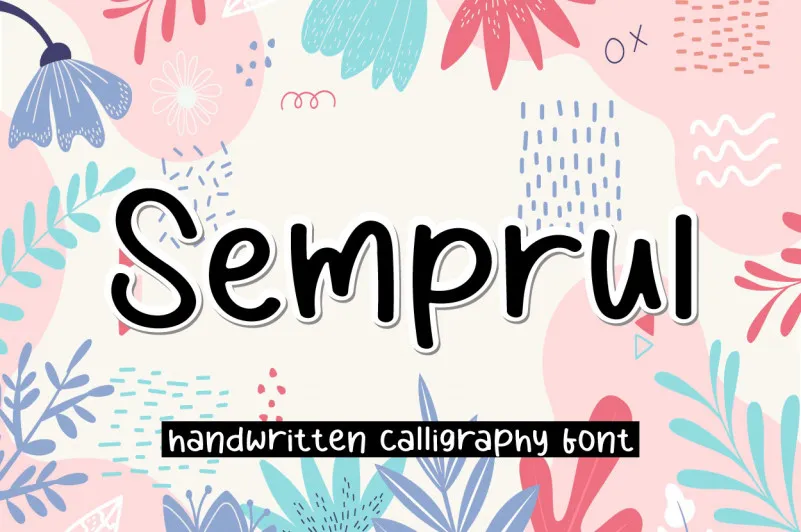
Semprul Script Font – Fonte Grátis
Semprul Script Font
A fonte Semprul Script Font oferece uma experiência única para designers brasileiros que desejam adicionar um toque personalizado aos seus projetos digitais. Com seu traçado elegante e natural, ela é perfeita para criar texturas agradáveis e harmonizar com qualquer estilo de design. Idealmente indicada para o público do Brasil, esta fonte oferece uma escrita cuidadosamente elaborada que ressoa com nossas tradicionais formas de expressão. Com um design envolvente e fluido, ela se adapta perfeitamente a qualquer projeto que exija graça e sofisticação. Além disso, sua elegância e simpatia garantem uma experiência visual agradável para quem utiliza a Semprul Script Font. Sugerido para designers brasileiros, a Semprul Script Font é um complemento indispensável ao seu estoque de fontes. Seja para criar materiais educacionais, conteúdo multimídia ou até mesmo design gráfico, esta fonte oferece o poder necessário para tornar seus projetos em verdadeiras obras de arte.